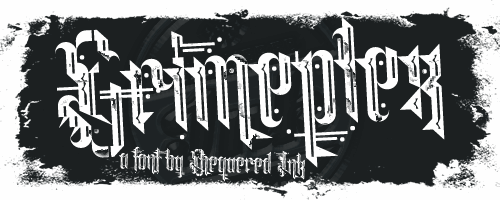
A fonte ‘Grimeplex’ é uma opção perfeita para quem está procurando por um efeito visual vibrante e único. Desenhada pelo designer Hamilton, a Grimeplex é perfeitamente adaptável aos estilos de exibição, trazendo destaque notável em qualquer design. A sua natureza bold e icônica torna-a ideal para o uso em materiais visuais que precisam de uma presença forte e imediata. Seja para gráficos publicitários, marcas ou até mesmo como título em um site corporativo, a ‘Grimeplex’ não decepcionará. Especialmente adequada à categoria de fontes de exibição, Grimeplex oferece os detalhes certos para criar uma identidade visual que chama atenção. Seja para personalizar seu logotipo ou aplicar em um layout web, esta font irá causar impacto. Não há dúvida de que a Grimeplex é mais do que apenas uma excelente escolha para uso pessoal; ela também está disponível para uso público mediante contribuição financeira através da PayPal. Nossa recomendação é experimentar a ‘Grimeplex’, seja para seu próximo projeto gráfico ou personalizado, e compartilhar o crédito com Hamilton, o designer incrivelmente talentoso que criou este poderoso recurso de fontes.